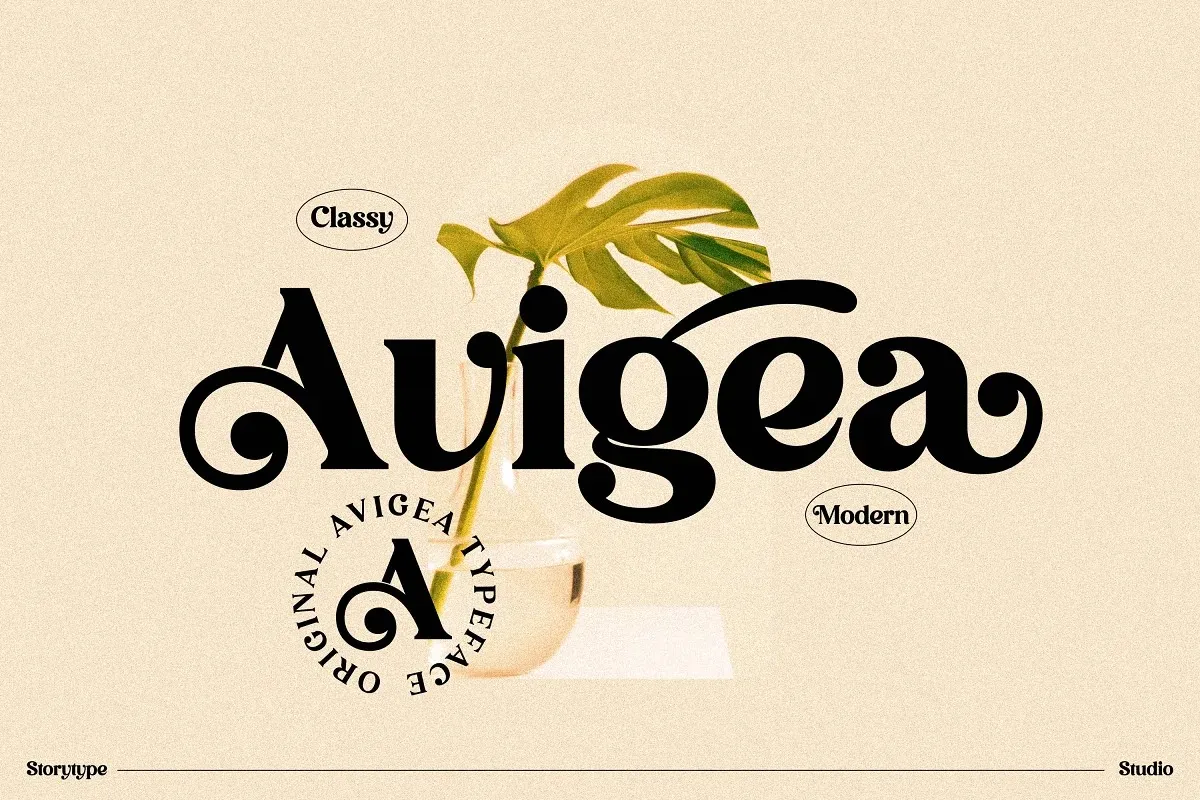
A Avigea Font é uma elegante tipografia serifada que traz um ar clássico e sofisticado aos projetos. Desenvolvida pela Storytype Studio, esta fonte foi criada para atender à necessidade de design gráfico sofisticados como logotipos luxuosos, títulos de livros ou filmes, marcas de moda, capas de revistas, cartazes, citações e muito mais. Perfeita para qualquer projeto que busque um toque refinado e de alto padrão, a Avigea atende a uma ampla gama de aplicações visuais. Seja no design de logotipos exclusivos ou em texturas gráficas elegantes, a Avigea oferece o estilo necessário para qualquer projeto que exija um toque sofisticado e moderno.